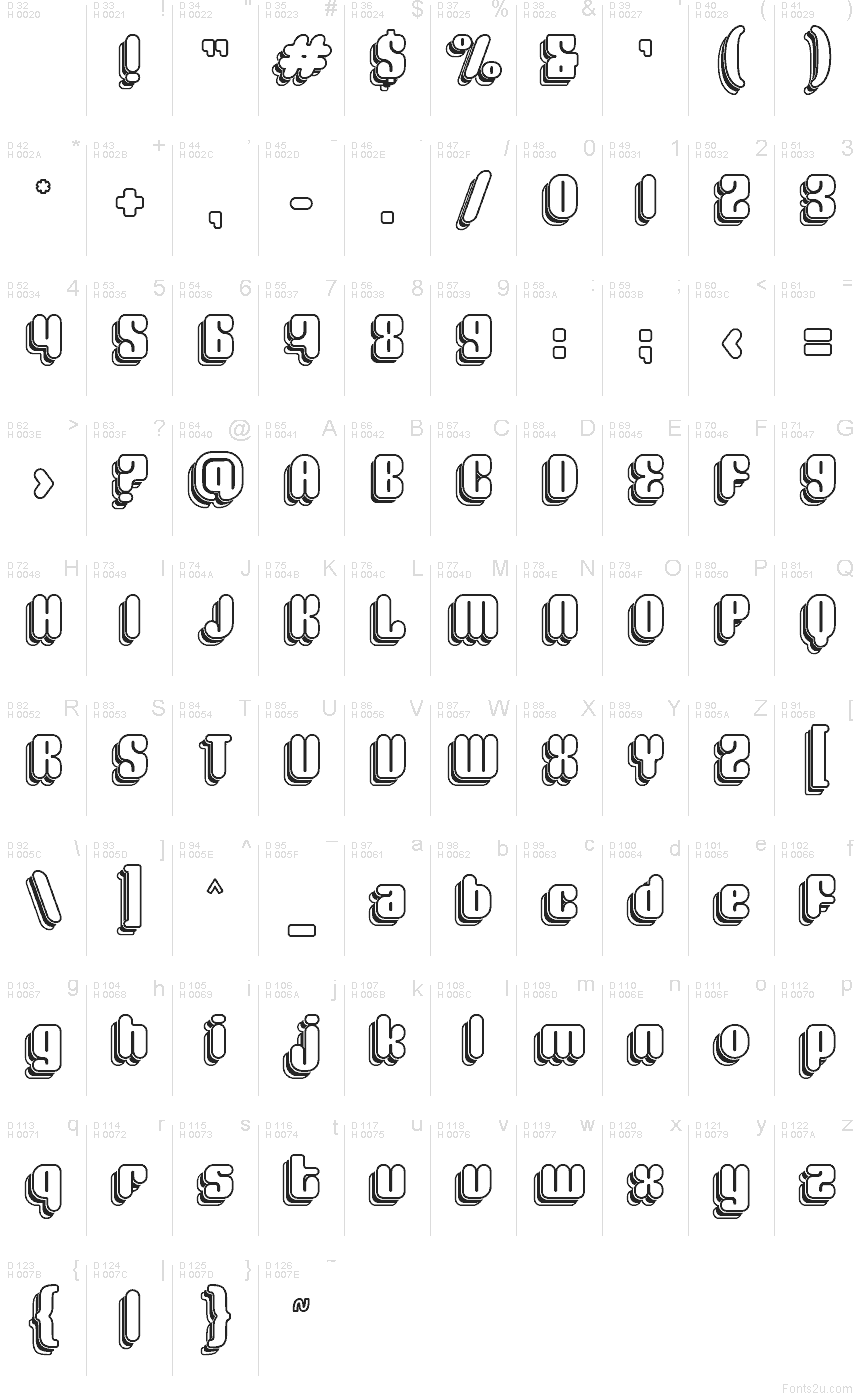
Dynamic Display Ten od Putracetol Studio je bezplatné 3D písmo v techno stylu, které definují měkké blokové tvary a odstupňovaný stín skládaný za každým písmenem jako u vrstvené světelné reklamy. Tato opakující se silueta dodává písmům objem a měkkost, zatímco úzké vnitřní výřezy zajišťují, že výsledek nepůsobí jako příliš jednoduchý „bublinový“ font.
Skvěle funguje v herních titulkách, grafikách aplikací, streamovacích překryvech, na plakátech či letácích k akcím, kde tato boční hloubka sama o sobě vytvoří silný vizuální efekt. Písmo je ideální také pro krátké brandingové řádky a návrhy log, zejména pokud hledáte zaoblený futuristický vzhled, který působí hravěji a plastičtěji než čistě uhlazené styly.